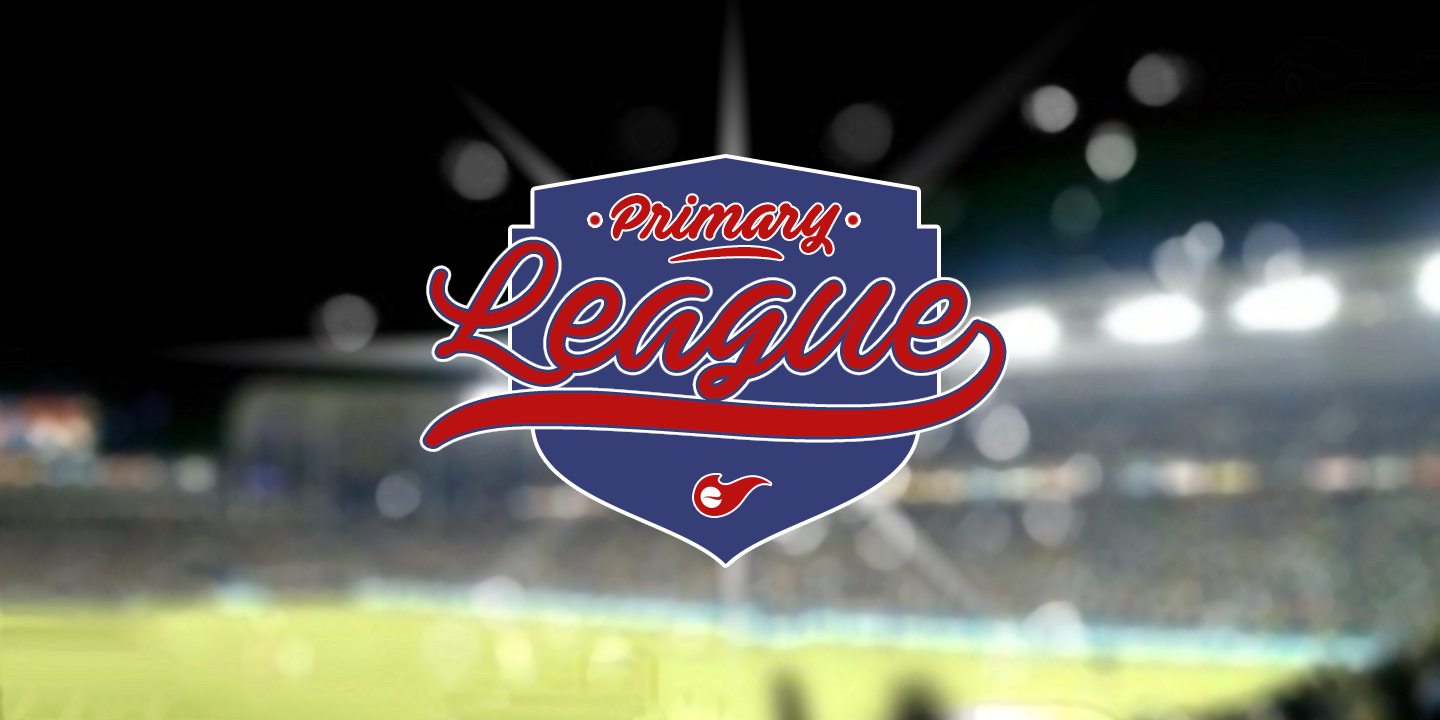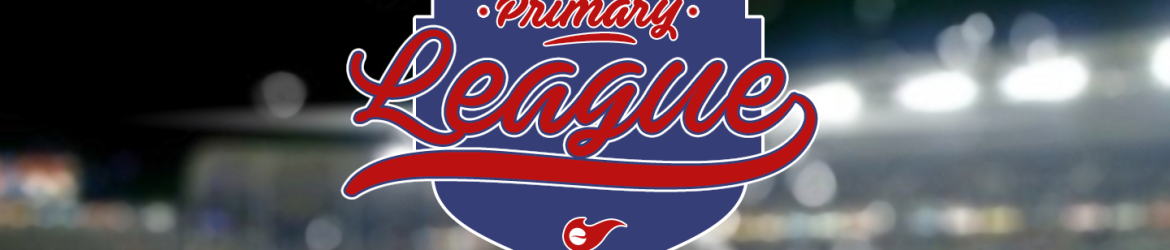
A Ave Utan Font é uma elegante escolha para aqueles que desejam adicionar um toque autêntico à sua obra de arte digital. Especialmente atraente para designers de gráficos, esta fonte cuidadosamente escrita foi criada pelo designer Hamilton e oferece um estilo único e envolvente. Perfeita tanto para textos formais quanto para designs mais artísticos, Ave Utan traz uma harmonia única que torna qualquer layout memorável. Com sua aparência delicadamente fechada e linhas sólidas, a fonte se adapta perfeitamente a diversos formatos de texto, desde headlines até parágrafos, garantindo sempre um acabamento cuidadosamente preenchido. Com sua variedade única de detalhes escritos à mão, Ave Utan oferece uma experiência de leitura que é tão sofisticada quanto autêntica. Seja para empolgantes cartazes ou delicadas capas de livros, esta fonte traz um toque refinado e moderno que certamente irá destacar seus projetos. Para adquirir uma licença comercial da Ave Utan Font, visite o site do designer: http://www.mansgreback.com/ave.